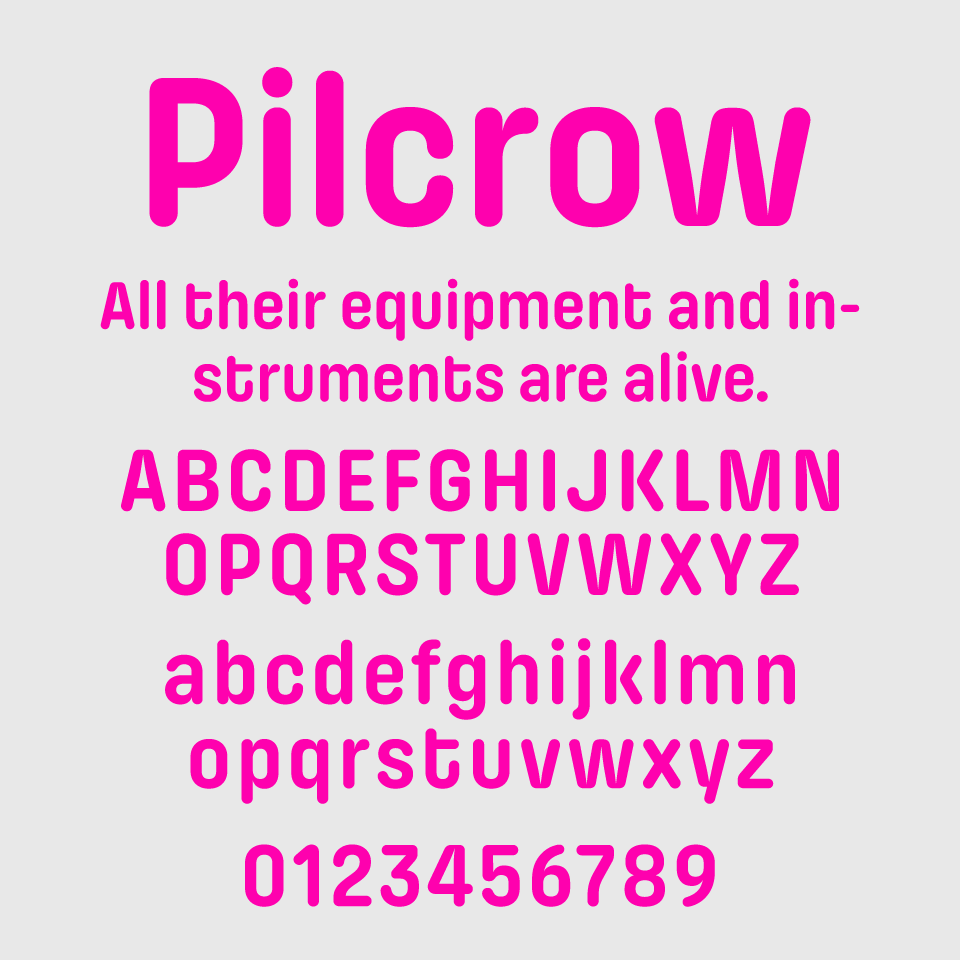
Pilcrow Roundedフォントは、モダンでかわいらしい印象のラウンド(丸ゴシック系)サンセリフフォントです。
文字の端に施されたわずかな装飾が特徴で、どこか愛嬌を感じさせます。とくに「g」や「k」などの個性的な形状が目を引きます。
柔らかくも元気なトーンを演出したいときに最適で、ビタミンカラーなどの配色とぴったりで、ポップなデザインやテック系スタートアップのロゴ、イベントのフライヤーなど幅広い用途にマッチします。